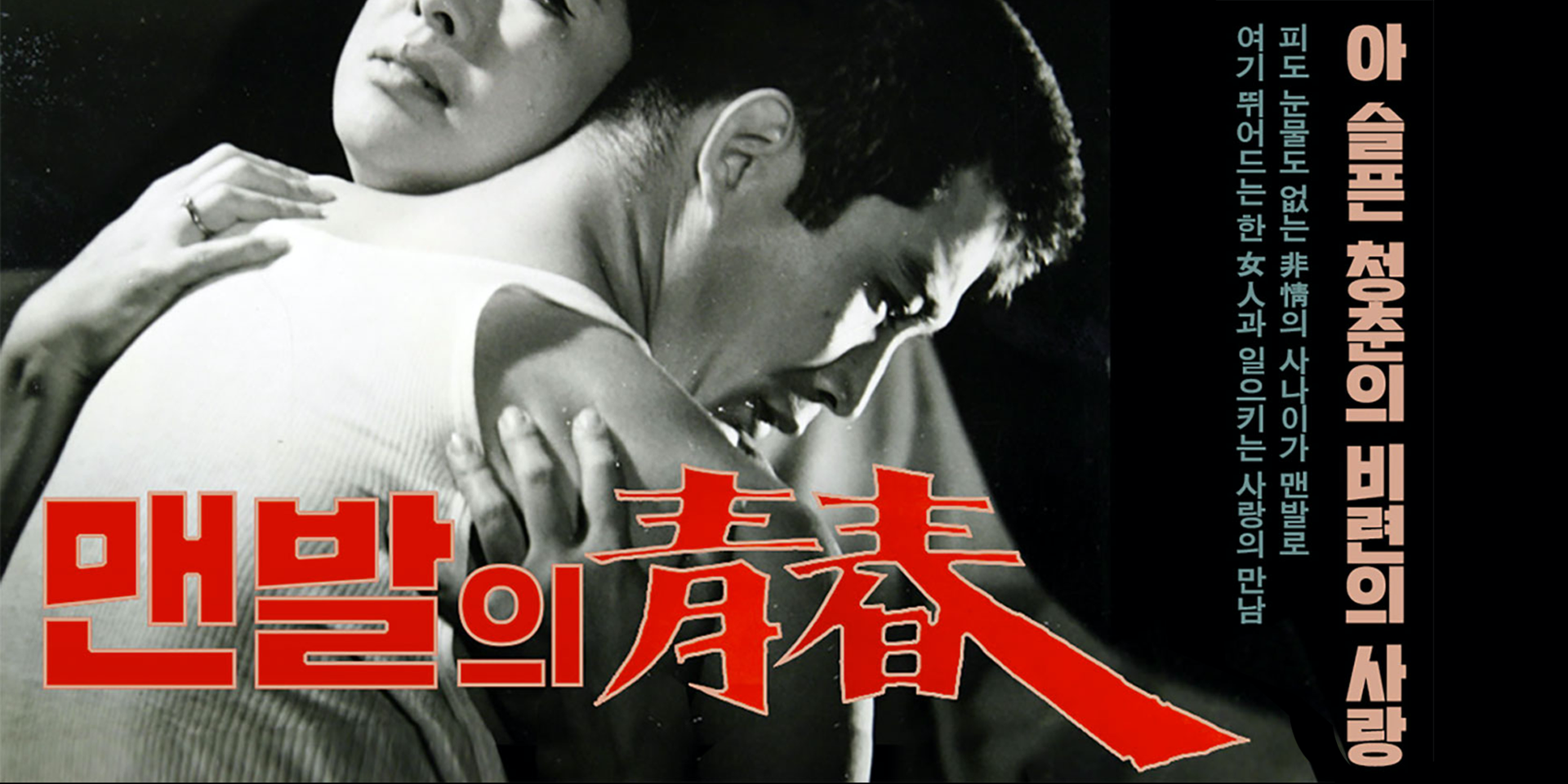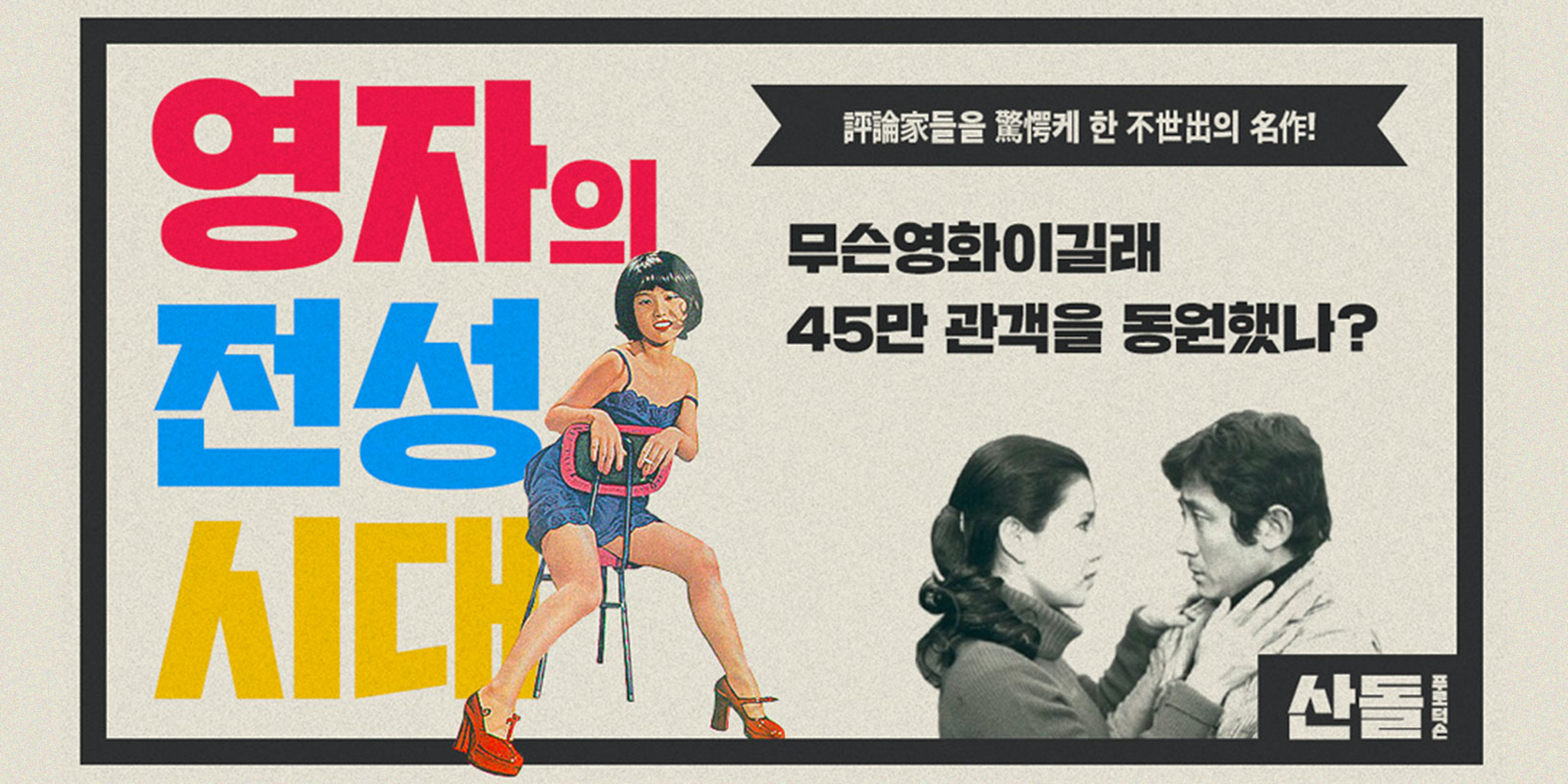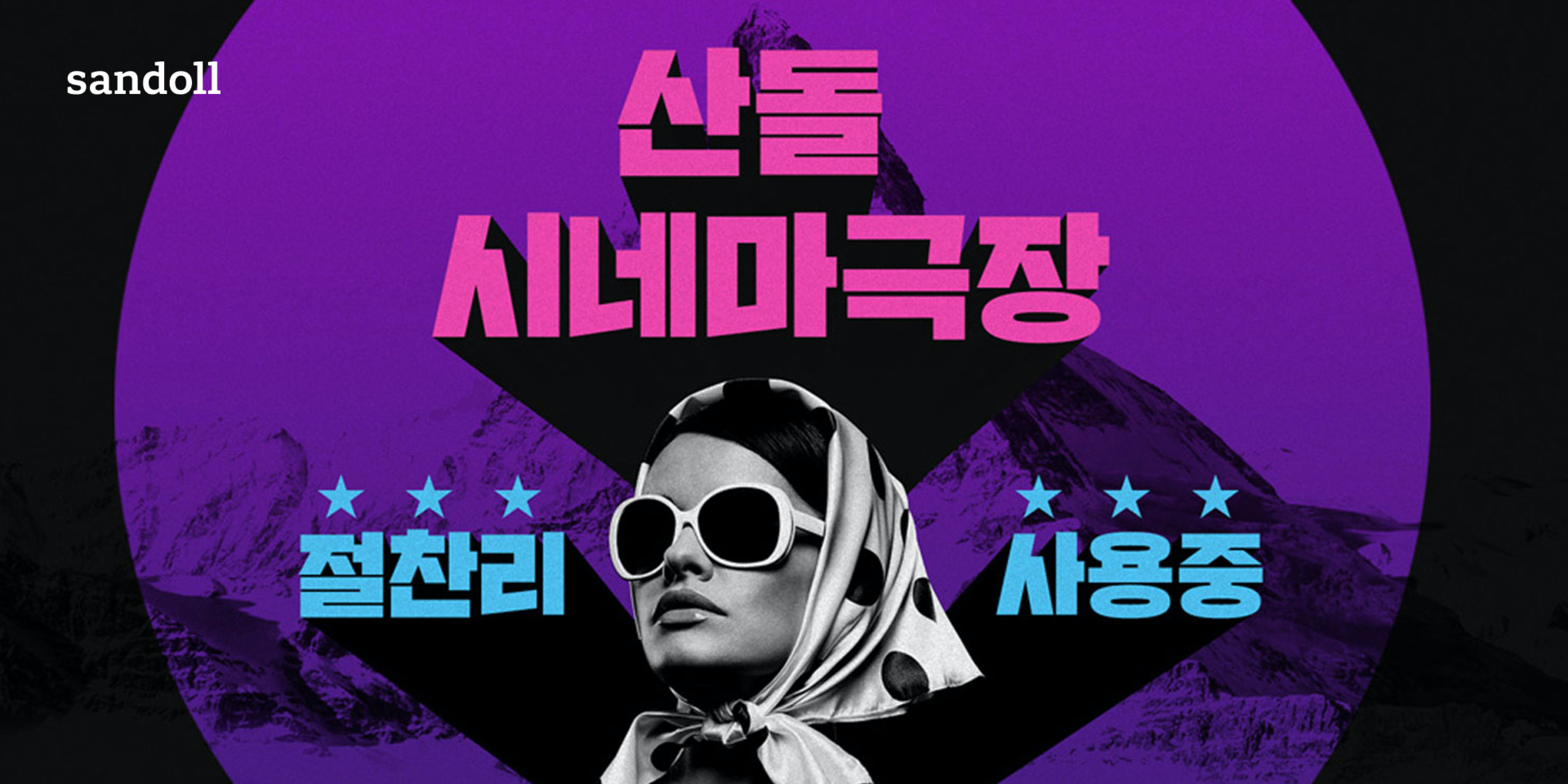
Sandoll 시네마극장
산돌 시네마극장은 60~70년대 극장가의 간판 속 느낌을 그대로 옮겨놓은 복고풍 폰트이다.한국판 그래피티의 느낌으로 거칠면서도 투박한 인상을 주며, 착시를 의도적으로 보정하지 않고 기계적인 규칙에 따라 획을 일률적으로 정렬하여 복고다운 투박함을 강조한 것이 특징이다.